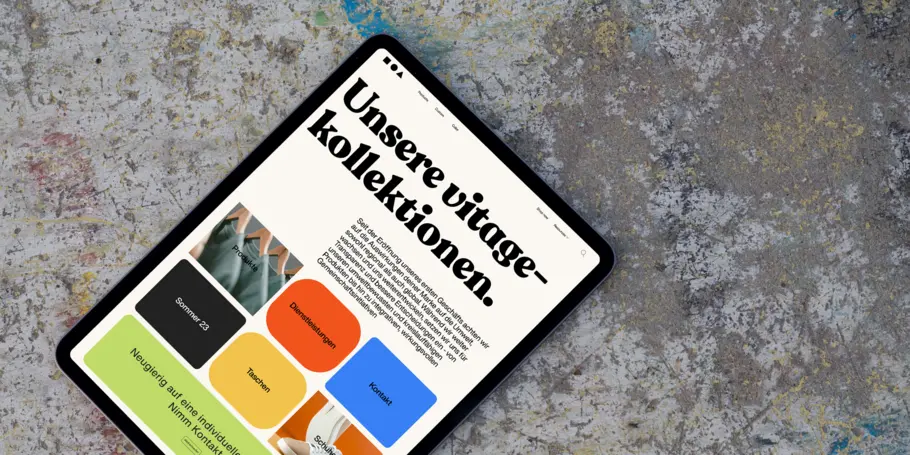
Keine nebulösen Geschäfte: 5 Tipps, wie du deine Marke digital fit hältst.
Meistert Ihre Hausschrift den Schritt von der stationären Filiale ins Internet ohne Störung? Sind die Texte in Ihrer mobilen App gut lesbar? Wie sieht es bei digitalen Anzeigen oder Bannern aus? Haben Sie Ihre visuelle Identität bereits in neueren Umgebungen wie dem Metaverse getestet?
Es ist keine leichte Aufgabe, die Omnichannel-Präsenz und die digitale Transformation einer Marke über alle Plattformen hinweg kohärent zu entwickeln, ganz gleich, ob Sie eine Webseite, Instagram-Anzeigen, eine App, ein VR-Erlebnis oder ein neues Spiel in einer virtuellen Arena produzieren.
Da die Verbraucher unentwegt von großen zu kleinen Bildschirmen und wieder zurück wechseln, ist es für den visuellen Auftritt von Marken entscheidend, hier mitzuspielen. Die Wahl der richtigen Schrift spielt dabei eine entscheidende Rolle. Schließlich sorgt ein konsistenter Markenauftritt über alle Berührungspunkte hinweg für ein hohes Maß an Vertrauen und ein authentisches Kundenerlebnis.
Wenn Sie also das nächste Mal ein Design für das aktuelle Marktgeschehen entwerfen, sollten Sie die nachfolgende Checkliste zu Rate ziehen, um sicher zu sein, dass Ihre Fonts im digitalen Zeitalter mithalten können, ohne zu vernebeln.
1. Check: Lesbarkeit
Dass ein Font am eigenen Schreibtisch perfekt lesbar ist, muss noch lange nicht heißen, dass das auch fürs Web oder für mobile Geräte gilt. Nervig? Ja. Aber lösbar! Ein Text aus einer Systemschrift oder einem Font, der mit einem Designprogramm geliefert und dort in puncto Laufweite und Zeilenabstand nachjustiert wurde, kann in einem anderen Kanal unscharf und holprig aussehen, was zu Irritationen gegenüber der Marke führt. Die Verbraucher sollten in der Lage sein, alle Ihre Texte in der digitalen Welt problemlos lesen zu können, sei es in einer App, einem Videospiel oder einer VR-Landschaft. Daher ist die Wahl einer Schrift, die weitsichtig entworfen und für alle Umgebungen optimiert und getestet wurde, absolut entscheidend.
2. Check: Ladegeschwindigkeit
Wenn Marken in der digitalen Landschaft mit ihren Kunden in Kontakt treten, gibt es einen funktionalen Aspekt zu berücksichtigen: Wie wirken sich die Font-Dateien auf die Ladezeiten einer Website aus? Wenn Sie auf Free Fonts setzen, die Sie im Netz gefunden haben, oder auf alte bzw. nicht web-optimierte Fonts, dann hat das garantiert negative Auswirkungen auf die Performance Ihrer Website.
Kunden haben keine Zeit, auf einen Seitenaufbau zu warten. Sie verlassen eine Webseite, wechseln zu einer anderen App oder beenden ein Videospiel, wenn die Ladezeiten zu lang sind. Um dies zu vermeiden, sollten Sie professionelle Fonts aus Quellen beziehen, die die Leistung Ihrer Produkte mit jedem neuen Technologiesprung optimieren, z. B. Web-Fonts der zweiten Generation oder Variable Fonts. Wenn Ihre Schriften immer auf dem neuesten Stand der Technik sind, müssen Sie sich keine Gedanken darüber machen, was unter der Oberfläche Ihrer typografischen Gestaltung passiert.
3. Check: Skalierung
Von der Überschrift auf einer Website bis hin zum Text auf dem Bildschirm einer Smartwatch: Die Verwendung von dynamischem Text, also einer Typografie, die sich je nach Layout oder Ausgabegerät automatisch anpasst, sollte für die digitalen Erlebnisse jeder Marke selbstverständlich sein. Im Web2 ist das bereits gang und gäbe, da viele dynamische Websites problemlos vom Desktop über das Tablet bis hin zum Handy skaliert werden können. Heute müssen Marken allerdings darüber nachdenken, wie ihre Schriften in kollaborativen, dezentralisierten Landschaften wie Web3 sowie in AR- und VR-Räumen erscheinen.
Dabei müssen Designer, aber auch Content-Manager in der Lage sein, einen Text schnell zu adaptieren, wenn sich eine Botschaft oder ein Konzept ändert. Dies geschieht tagtäglich auf Nachrichten-Websites, bei Spiele-Updates oder im Einzelhandel, wenn die Preise aktualisiert werden. Im Online-Bereich ist nichts mehr statisch. Der Einsatz eines Variable Fonts, gesteuert via CSS, bedeutet, dass man effizient und schnell Änderungen vornehmen kann, ohne sich Gedanken über die Auswirkungen auf das Layout machen zu müssen.
4. Check: Rendering
Ein weiterer Aspekt der Funktionalität von Schriften, der nicht übersehen werden darf, ist das Rendern von Texten am Bildschirm. Das Thema ist kompliziert, vor allem, wenn es um die Entwicklung von Apps und Wearables oder um die Erstellung digitaler Inhalte geht, die möglicherweise kritische Zeichen enthalten. Rendering-Probleme treten auf, wenn die Groß- und Kleinschreibung über einen Stil-Befehl gemanagt wird, wenn ein Font nicht ordentlich gehintet ist oder wenn das Design einer Schrift nicht für den Bildschirm geeignet ist (zu feine Haarlinien, zu zarte Serifen oder zu kleine Buchstabeninnenräume). Derartige Probleme werden zu einer besonderen Herausforderung, wenn es um die Darstellung von Fremdsprachen geht. Erfahrene Designer erkennen sofort, wenn das Rendering nicht stimmt. Verpixelte Schriften oder unkalkulierbare Umbrüche sind ein absolutes No-Go für eine Marke. Verunsicherte Kunden fragen sich, ob sie eine Lesebrille benötigen. Ganz zu schweigen von den Anforderungen an Barrierefreiheit, die moderne Websites erfüllen sollten. Das Ziel kann daher nur sein, sich als Marke für professionelle, vertrauenswürdige Schriften zu entscheiden, die ästhetisch und technisch allen Anforderungen an die Lesbarkeit auf Bildschirmen jeder Größe gewachsen sind.
5. Check: Branding
Bislang haben wir funktionale und gestalterische Aspekte behandelt, die für eine klare, lesbare und schnell ladende Typografie auf allen Geräten sorgen. Letztendlich geht es dabei um die Darstellung der Marke. Wenn eine Schrift, die für Print verfügbar ist, nicht als Web-Font verfügbar ist (.woff oder .woff2), müssen sich Web-Entwickler mit Kompromisslösungen herumschlagen, die nicht auf der Höhe der Zeit und erst recht nicht zukunftssicher sind. Manche kommen damit durch, aber nicht selten endet es auch im visuellen Chaos. Ein inkonsistentes Markenerlebnis, ob im Gedruckten oder digital, erzeugt bei den Verbrauchern eine Akzeptanzlücke: Bewusst oder unterbewusst entsteht Misstrauen und damit eine nachlassende Verbundenheit mit der Marke.
Marken können dieses Problem vermeiden, indem sie von vornherein Schriften wählen, die in analogen und digitalen Umgebungen gleichermaßen gut funktionieren. Wie wir alle wissen, ist das angesichts der Tatsache, dass sich die Kommunikation gerade kopfüber in eine Mixed-Reality-Zukunft stürzt – Metaverse, du bist gemeint –, besonders wichtig. Die Aufgabe von Designern ist es, das Markenerlebnis ohne Brüche zu gestalten, und dafür ist die Schrift das Fundament.
Font-Checkliste für digitale Projekte
- Beste Lesbarkeit, überall
- Kurze Ladezeiten
- Dynamische Fonts
- Unverfälschte Buchstabenformen
- Passend zur Marke